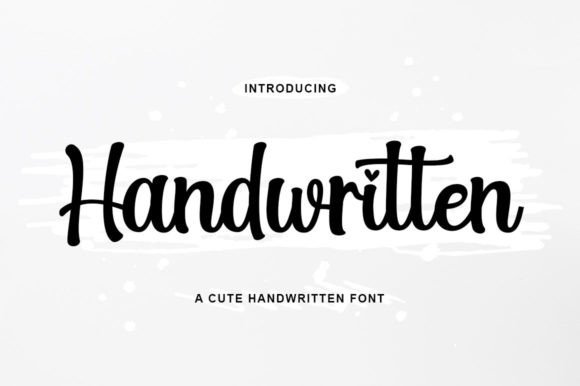
Handwritten
Présentation de la police Handwritten
Handwritten est une police de caractères scriptée bouncy et mignonne qui apporte une touche ludique et quirky à n'importe quel projet de design. Que vous créiez des invitations de mariage, des cartes d'anniversaire, des designs pour t-shirts ou des autocollants, cette police manuscrite amusante donne vie à vos créations avec un style décontracté et amical.
Pourquoi Handwritten est votre meilleur choix
Cette police offre un parfait équilibre entre facilité de lecture et style, ce qui en fait un outil polyvalent pour les graphistes débutants et expérimentés. Son caractère rebondie et playful ajoute de l'énergie sans sacrifier la clarté, ce qui la rend parfaite pour :
- Designs de invitations de mariage et de cartes de félicitations
- Creations de cartes d'anniversaire et de bannières de fête
- Impressions de designs pour t-shirts et de merchandise
- Projets de crafting, de création d'aut